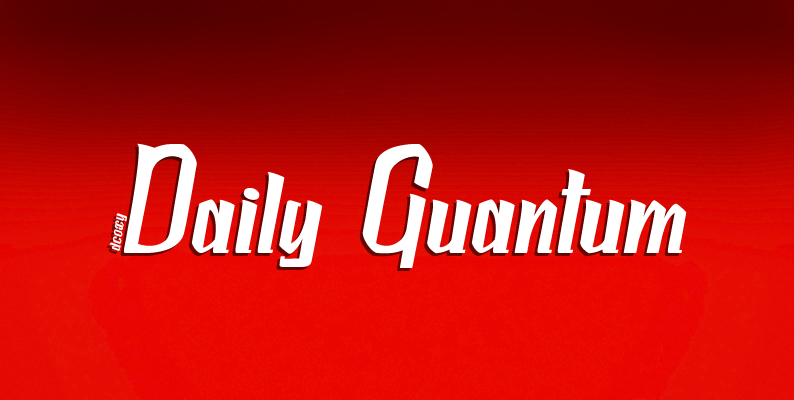
A Daily Quantum Font é uma tipografia de destaque projetada pelo designer Hamilton, perfeita para ambientes de design que buscam impacto visual. Este tipo digital apresenta linhas levemente distorcidas e formas geometricamente complexas, criando um design vibrante que se adapta perfeitamente a qualquer projeto de mídia visual. Com sua configuração fluida e versátil, essa fonte foi projetada para destacar mensagens em ambientes comerciais ou promocionais. Seja você um designer gráfico ou uma empresa em marketing, o Daily Quantum Font é sua ferramenta ideal para estabelecer um visual único. A licença requerida significa que esta fonte deve ser usada apenas em propósitos não-comerciais ou quando a fonte for adquirida com um contrato de licenciamento. Para mais informações sobre como usar, entre em contato conosco no endereço: